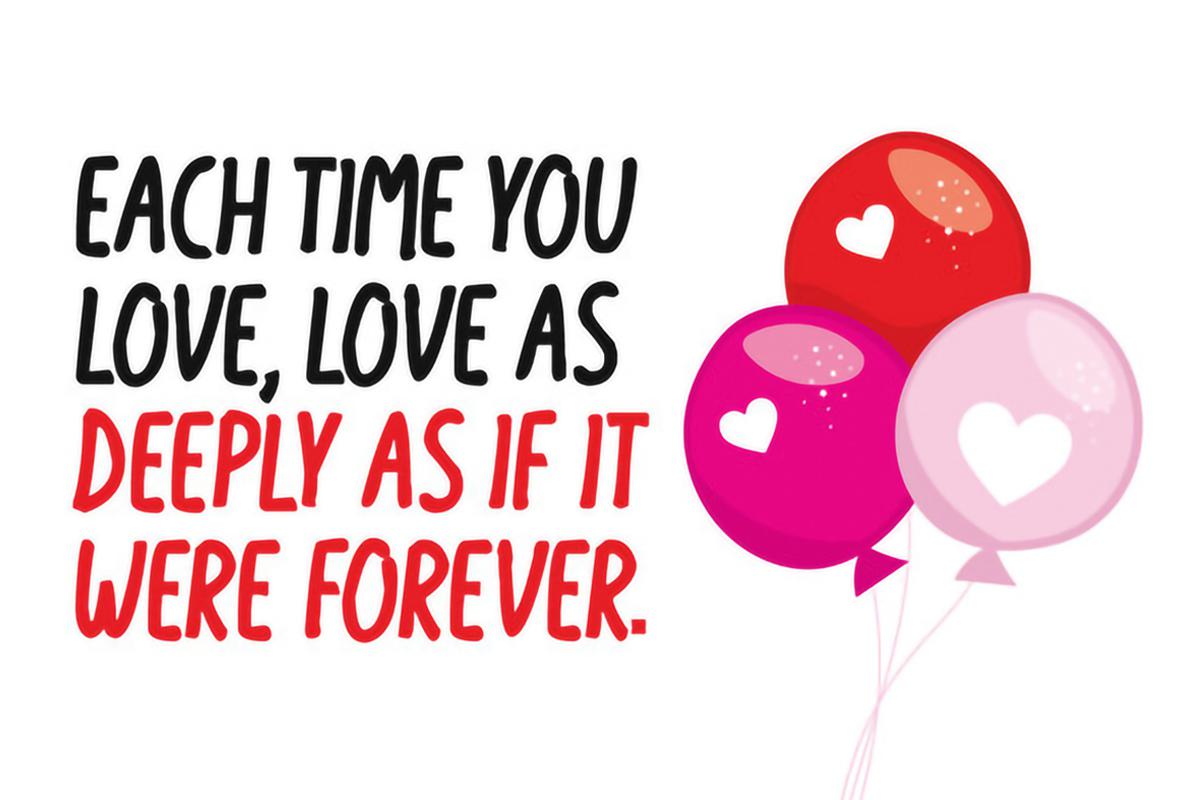
FreeValentine Monsters Font是为Valentine Moment设计的显示Font。它保存了与Valentine相关的所有项目的良好外观Font。因此,作者创建了此Font,并具有特殊的字符来呈现Wesome Moment。此Font适用于传单、t恤、横幅、别针、钥匙链、贴纸、商品、,还有更多。安装到您的任何设备上都可以使用它,它带有两个格式文件,这两个格式文件将使您能够根据您的设备使用情况进行调整。但是,此演示模式可用于个人许可证,但您可以从购买PremiumVersion获得更多功能。